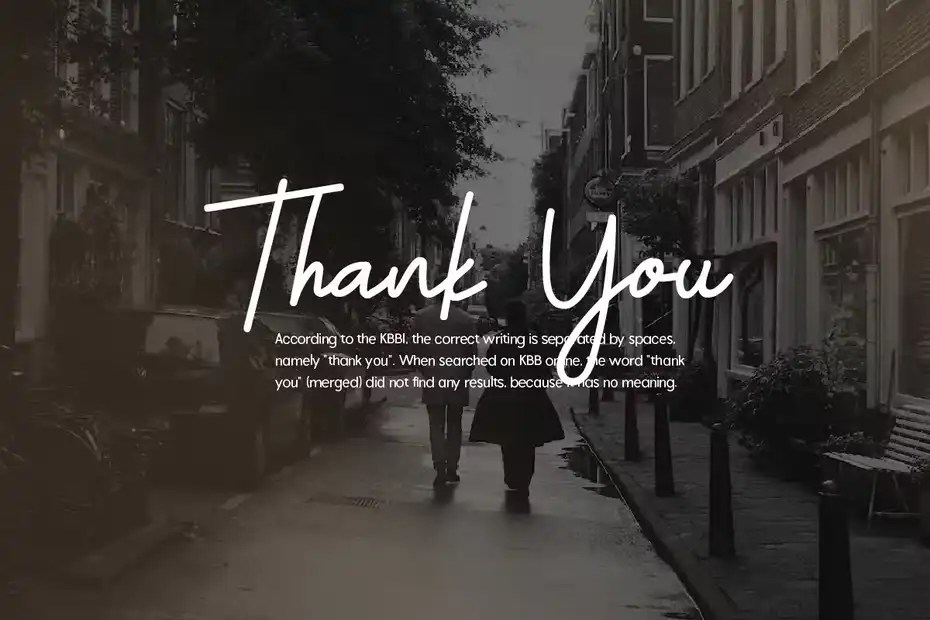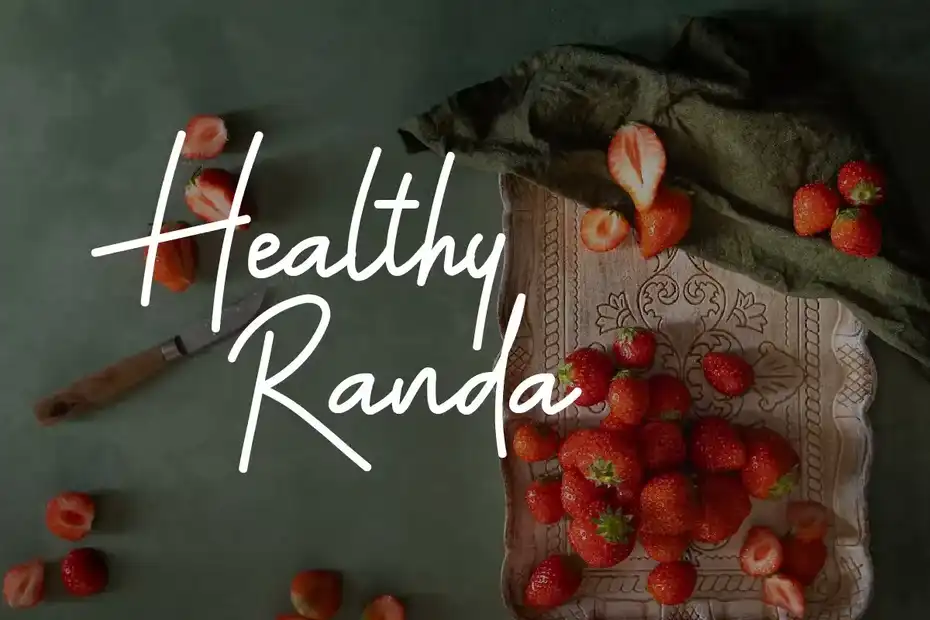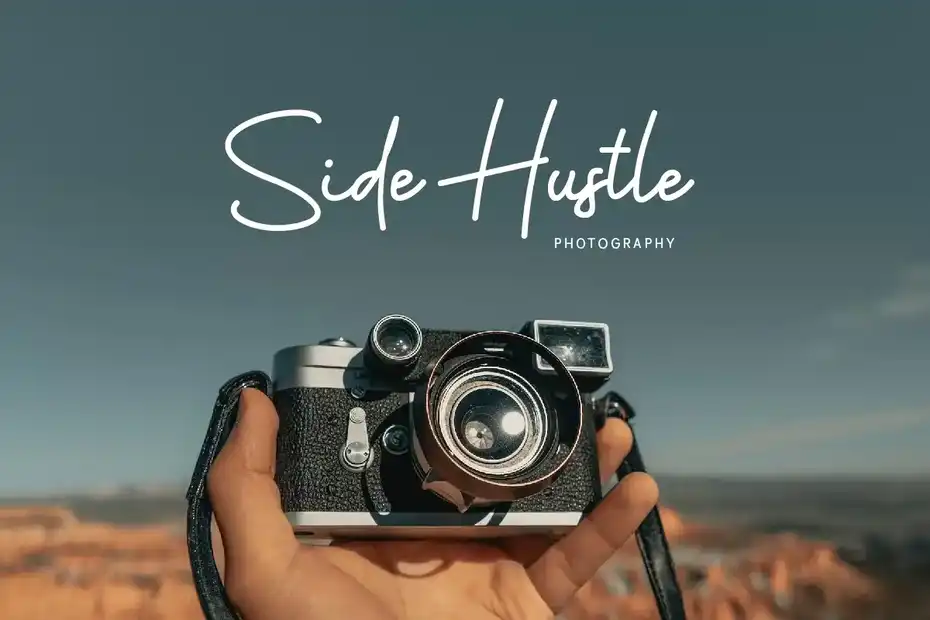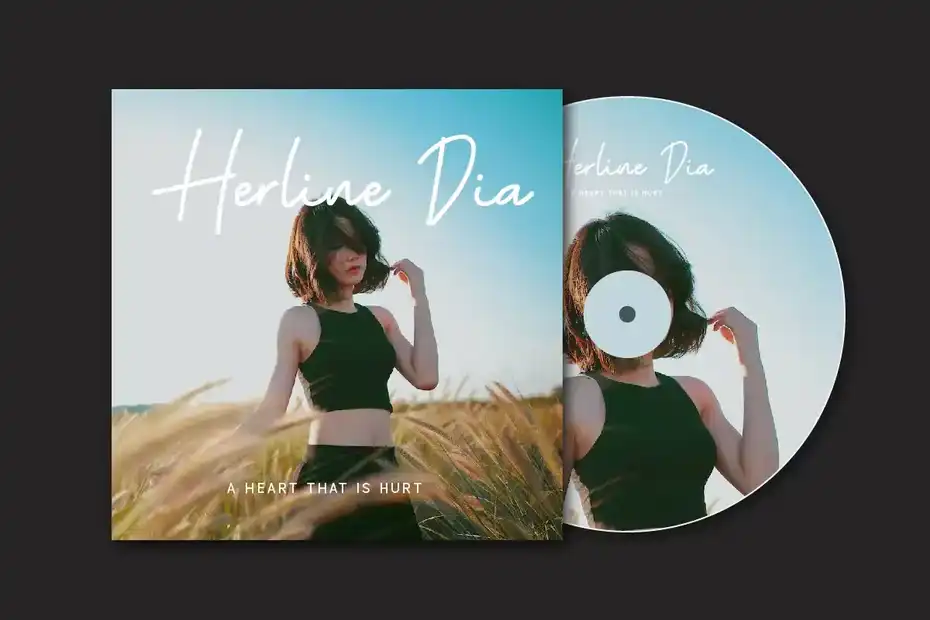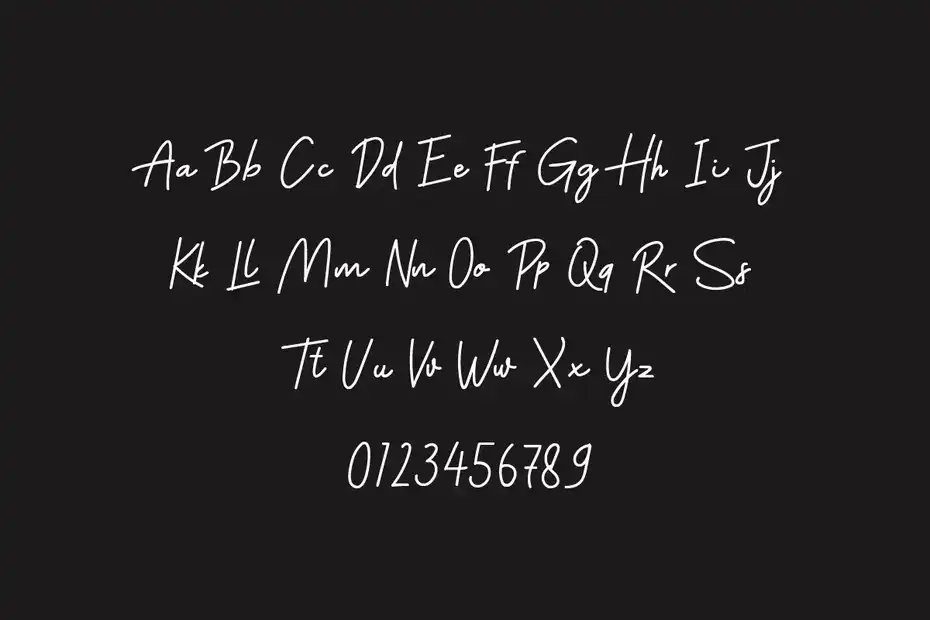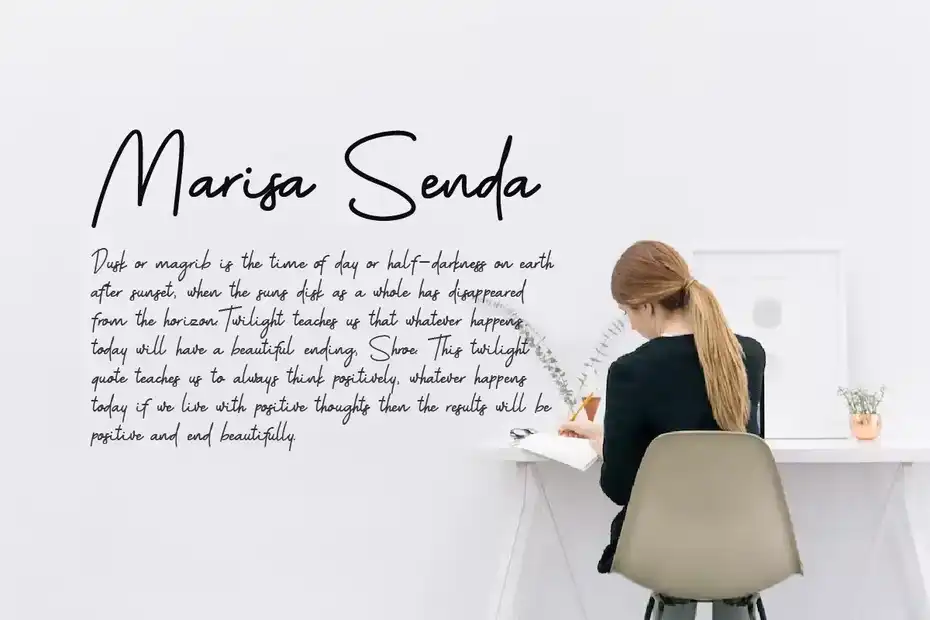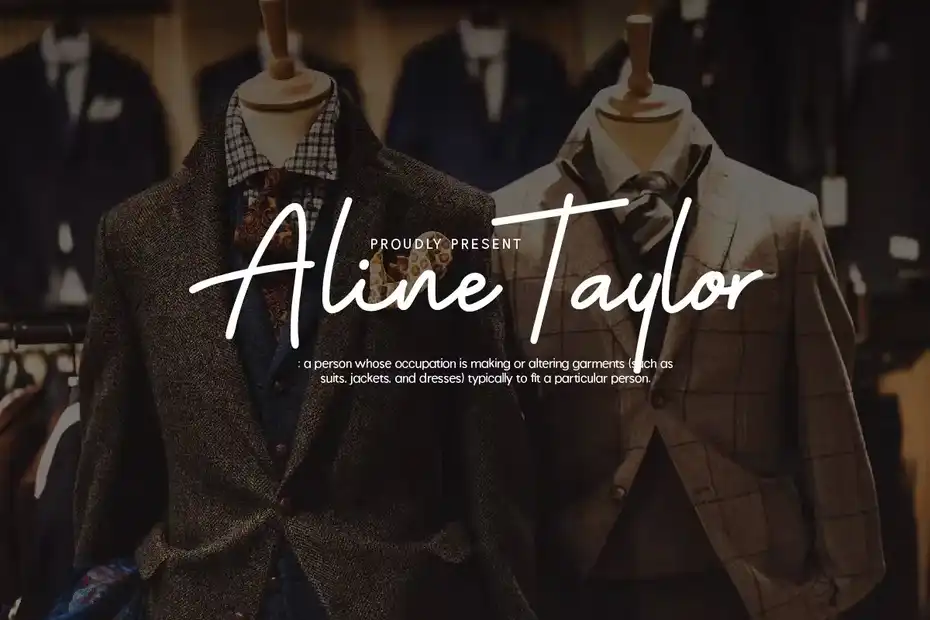
دانلود فونت انگلیسی به سبک امضا Hello Dine Signature Font
فونت انگلیسی به سبک امضا Hello Dine Signature Font : این فونت یک فونت دست نویس به سبک امضا است که برای پروژه های برندینگ، لوگو، کارت عروسی، پست شبکه های اجتماعی، تبلیغات، بسته بندی محصول، طرح های محصول، برچسب، عکاسی، واترمارک، دعوت نامه و غیره مناسب میباشد.
فونت انگلیسی به سبک امضا Hello Dine Signature Font - 1
فونت انگلیسی به سبک امضا Hello Dine Signature Font - 3
فونت انگلیسی به سبک امضا Hello Dine Signature Font - 5
فونت انگلیسی به سبک امضا Hello Dine Signature Font - 7
فونت انگلیسی به سبک امضا Hello Dine Signature Font - 9
فونت انگلیسی به سبک امضا Hello Dine Signature Font - 11
فونت انگلیسی به سبک امضا Hello Dine Signature Font - 13